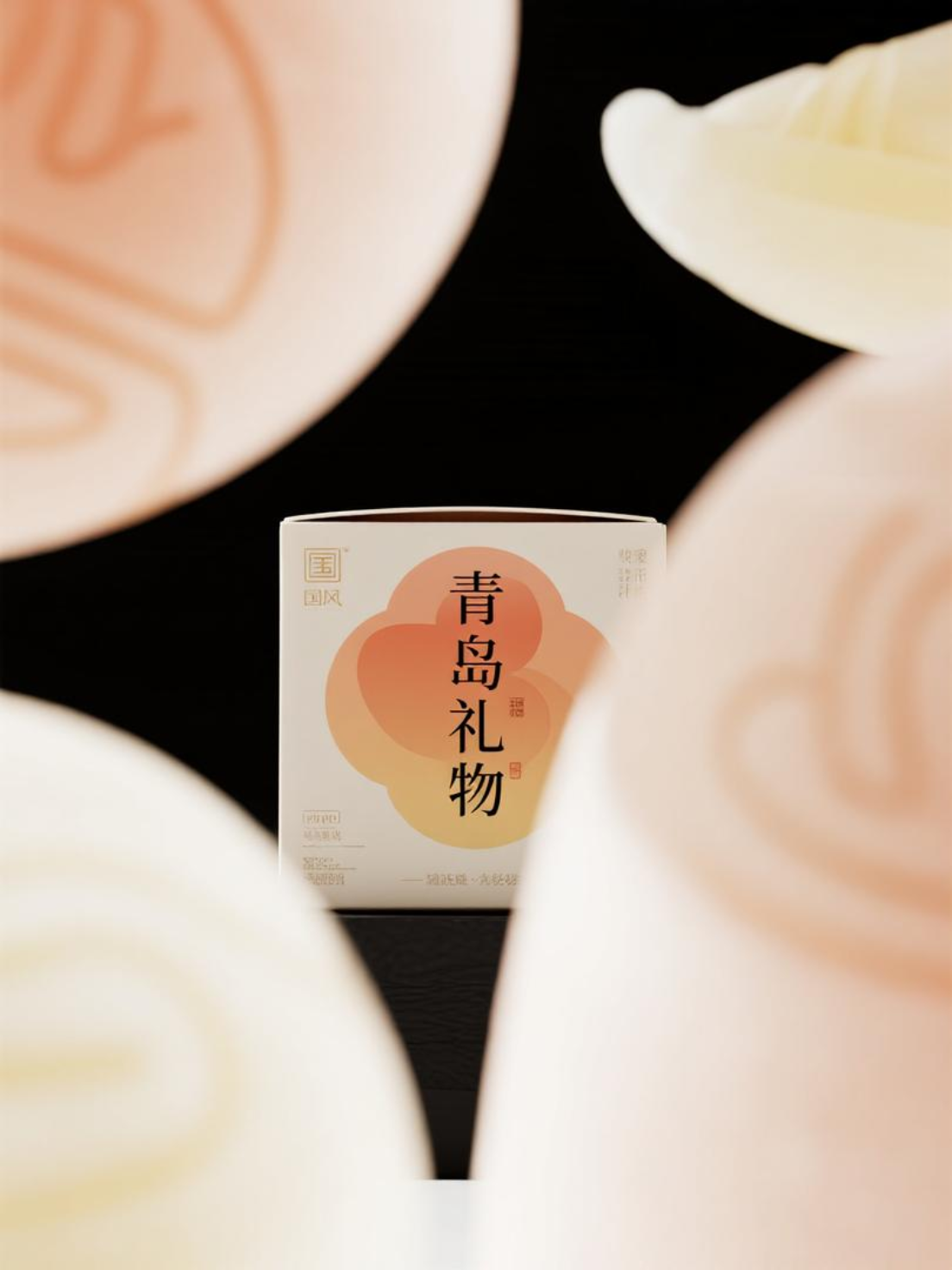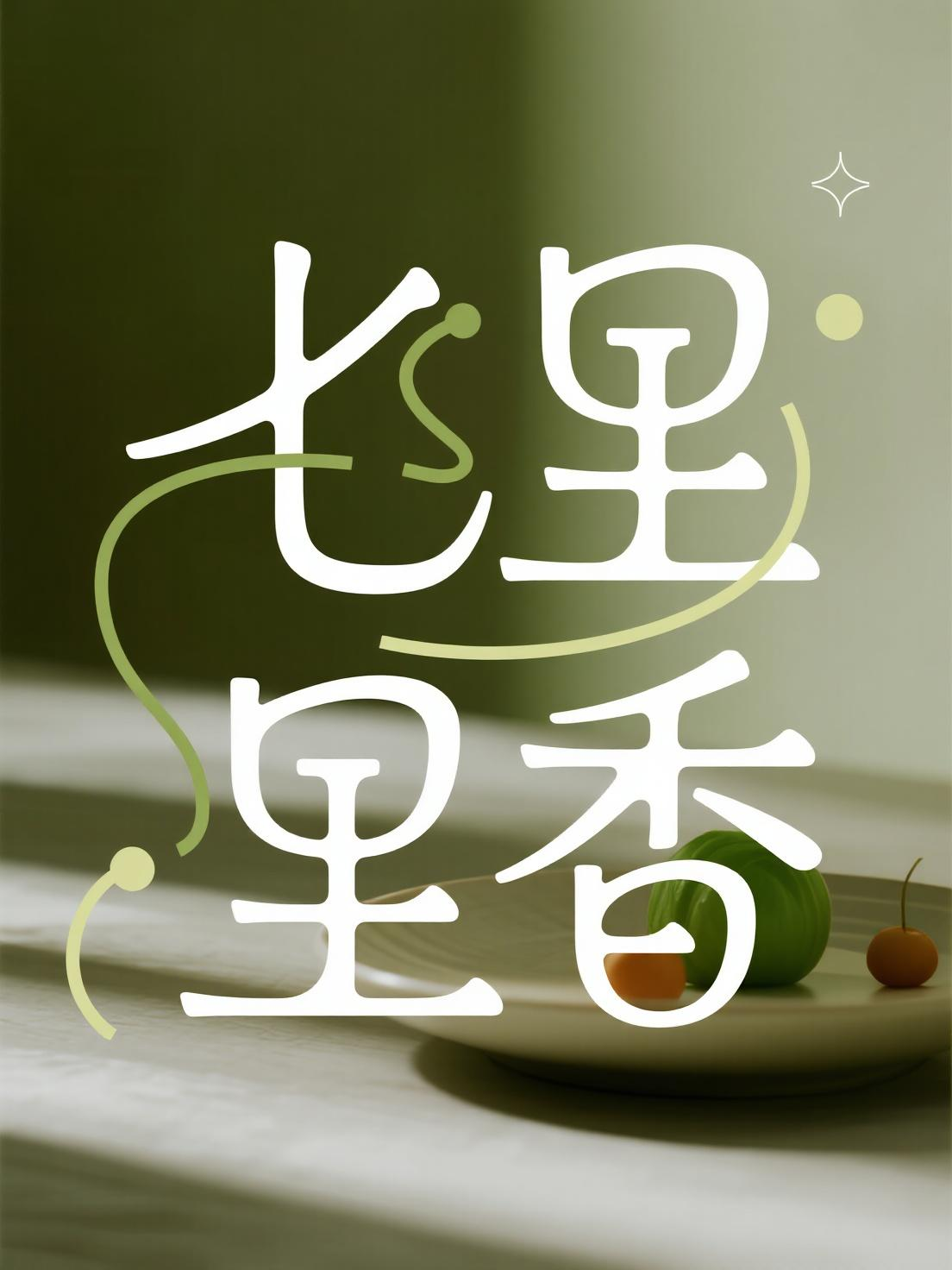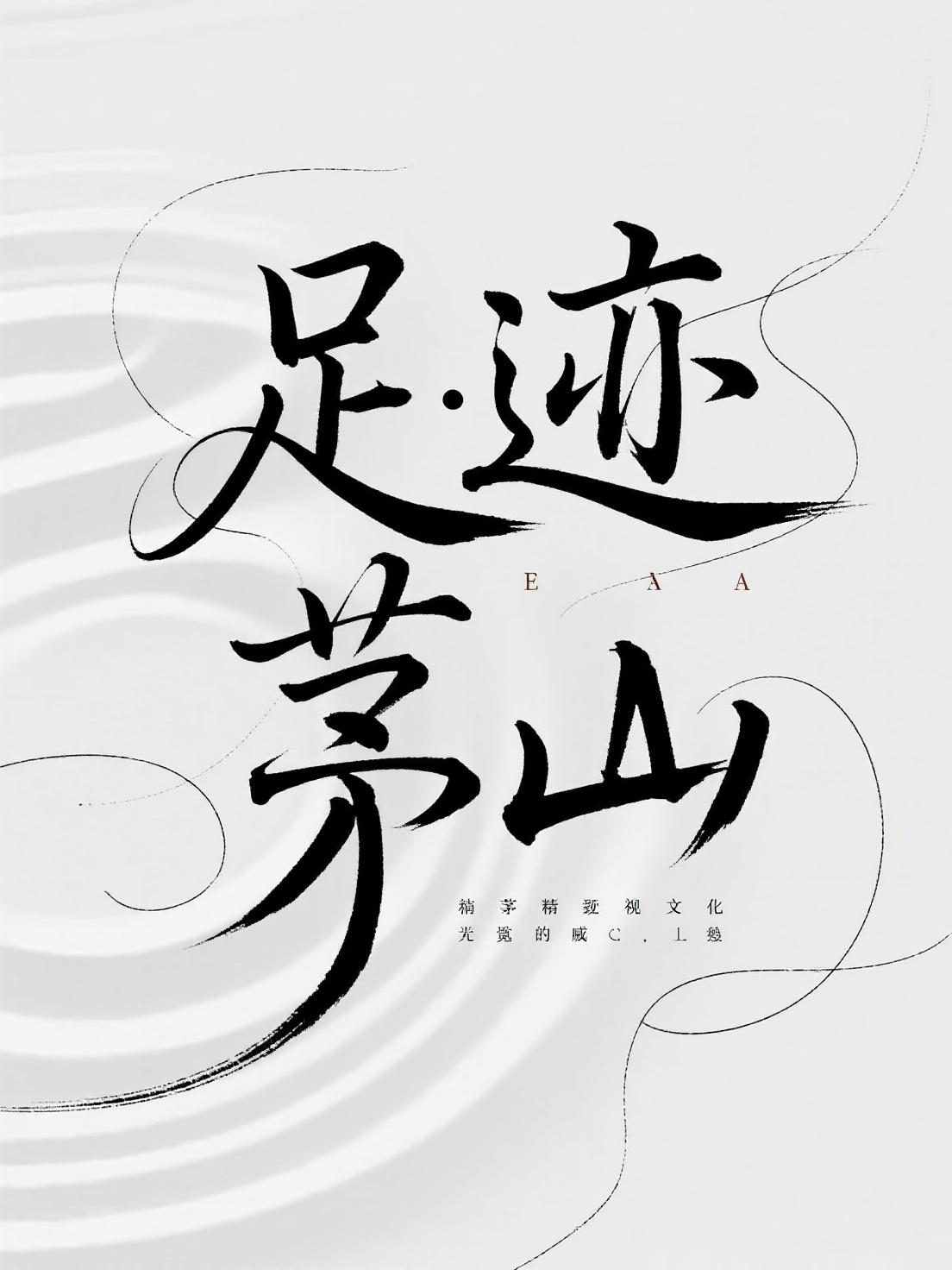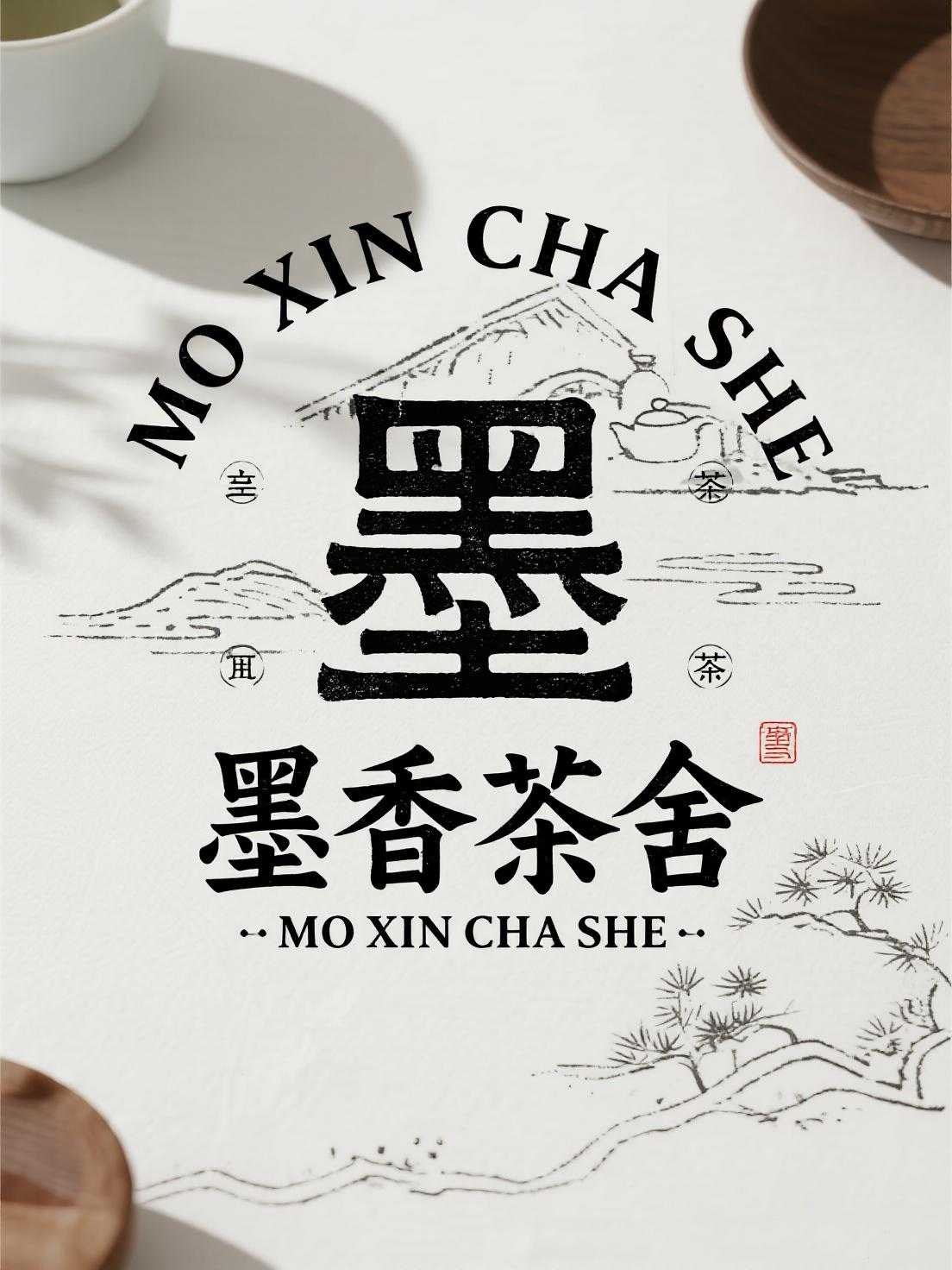
关于字体设计,您可能需要了解这些~~
字体绝非装饰细节,而是品牌沟通的基石、用户体验的门槛和商业价值的守护者。忽视字体问题,等同于放任法律风险、浪费营销投入、阻碍用户转化、损害品牌声誉。那些因字体流失的客单、关闭的页面、失望的用户,都在无声控诉着企业对视觉体验的漠视。
为什么字体设计为其他设计的基础呢?
字体设计,是视觉设计领域那“看不见的手”。它构建秩序、传递情感、塑造品牌、跨越媒介、承载文化。它不是设计流程中最后添加的“装饰品”,而是构思之初就必须深思熟虑的战略起点。
字体系统的构建,绝非简单的“选个好看的字”。它是融合法律合规、品牌战略、用户体验、技术实现的复杂系统工程,是品牌在数字丛林中构建差异化、提升认知效率、赢得用户忠诚的核心基础设施。
数字时代的字体美学:从像素到情感共鸣
未来的字体或许不再是固定形态,而是能感知用户情绪、适配场景需求的“活的符号”。从敦煌写经体的飞白笔触到区块链上的NFT字体,字体设计始终在记录时代精神,也在创造新的文明形态。在这个每个像素都承载情感的时代,字体设计师既是技术的驾驭者,更是文化的摆渡人。